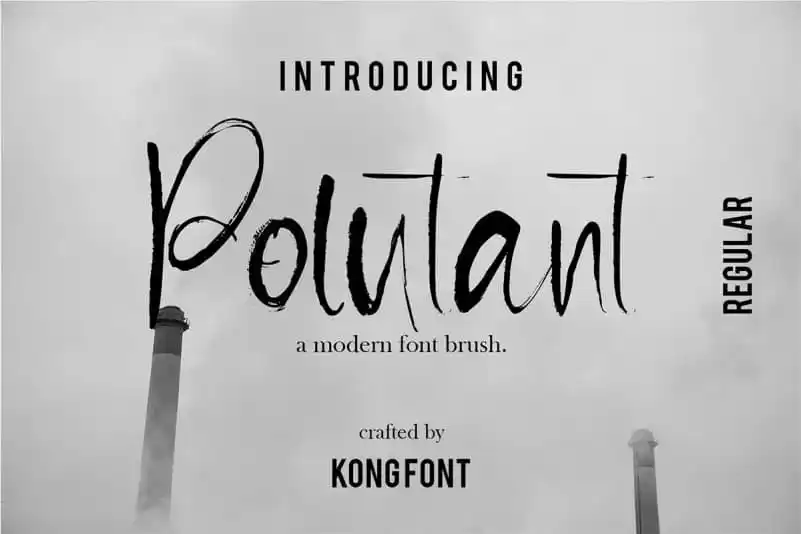
Pollutant Brush Font – Download Grátis
A ‘Pollutant Brush Font’ é uma elegante tipografia escrita à mão com traçado seco que traz a essência de um estilo natural e único. Suas linhas suaves e seus traços não retos criam uma aparência amigável, perfeita para diversos projetos gráficos. Esta fonte é ideal tanto para marcas de luxo como para designs editoriais ou para o design de estaçãoais. Além disso, ela se destaca em niches que incluem elegante moda moderna, beleza feminina, propaganda online, cartas de convite e decoração residencial. A ‘Pollutant Brush Font’ também é ideal para criações artísticas, citações, capas de livros e até mesmo eventos especiais como casamentos e festas de aniversário. Com suas características únicas, esta fonte oferece uma variedade imensa de possibilidades para designers em diferentes campos da arte.